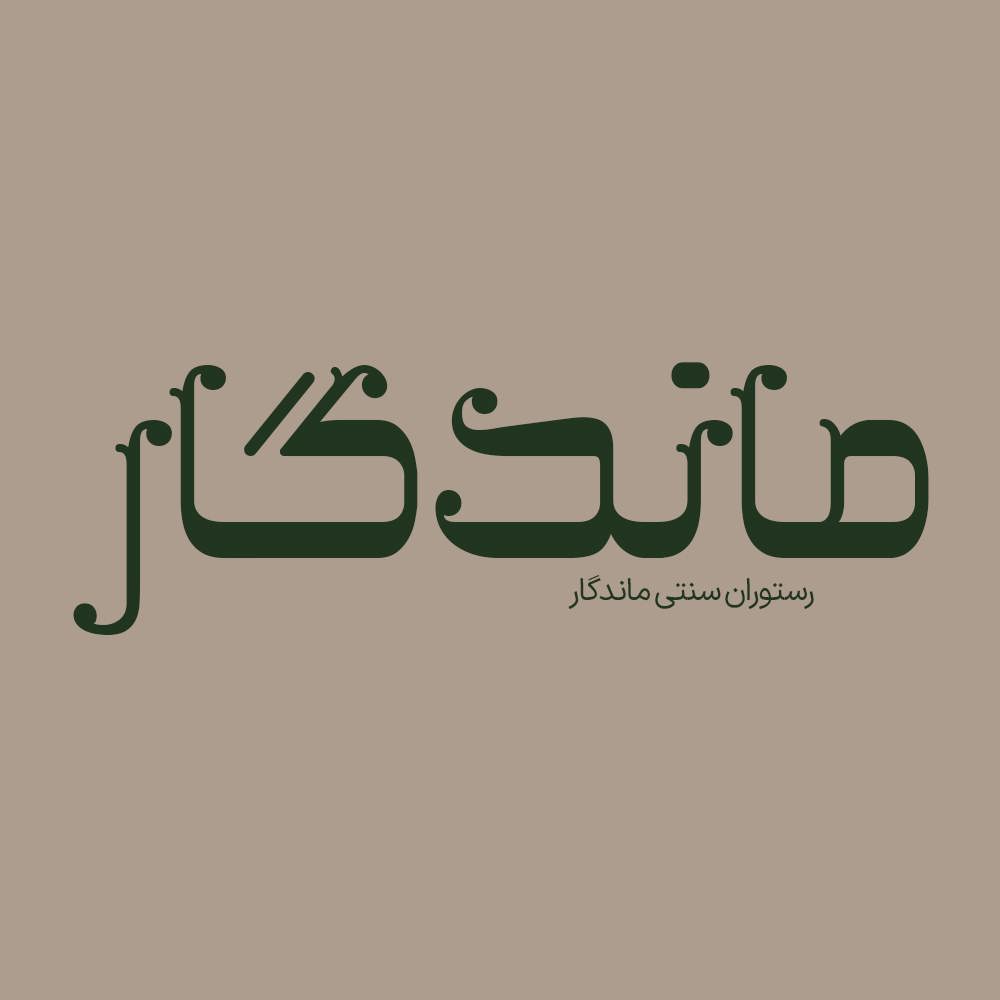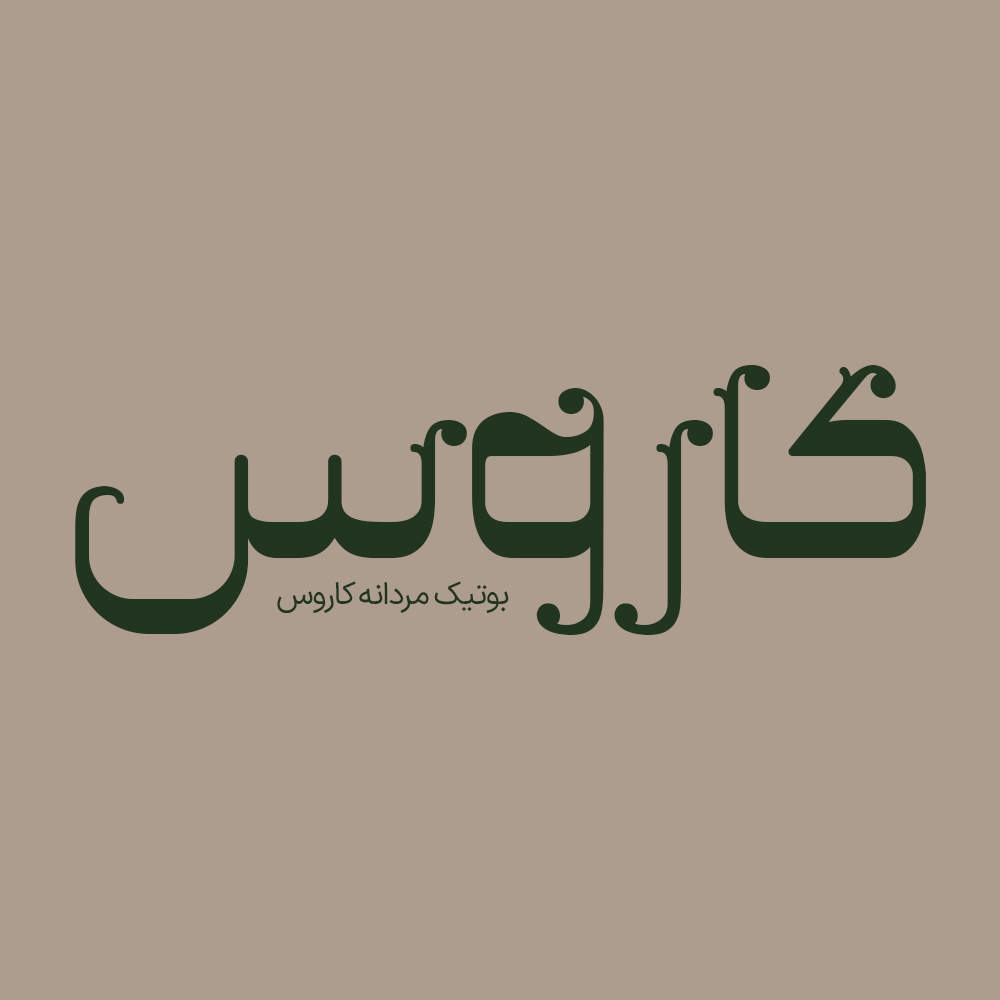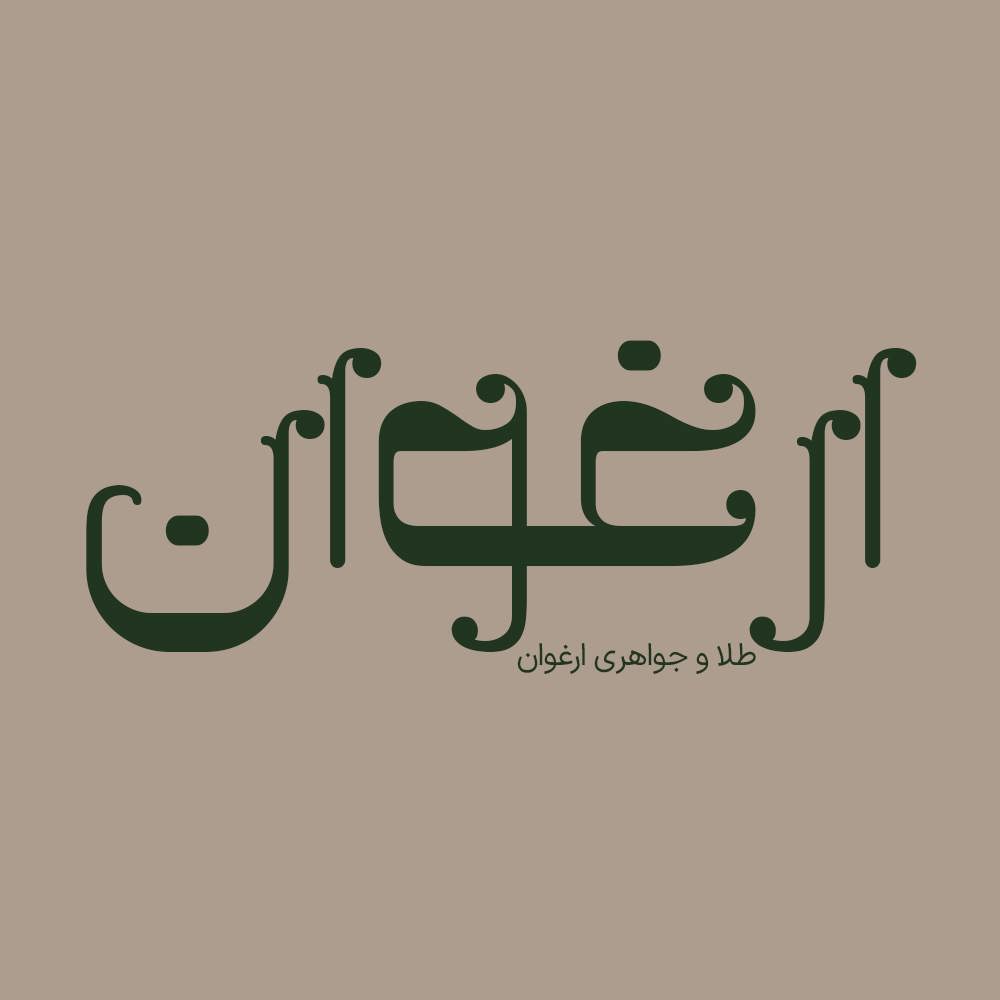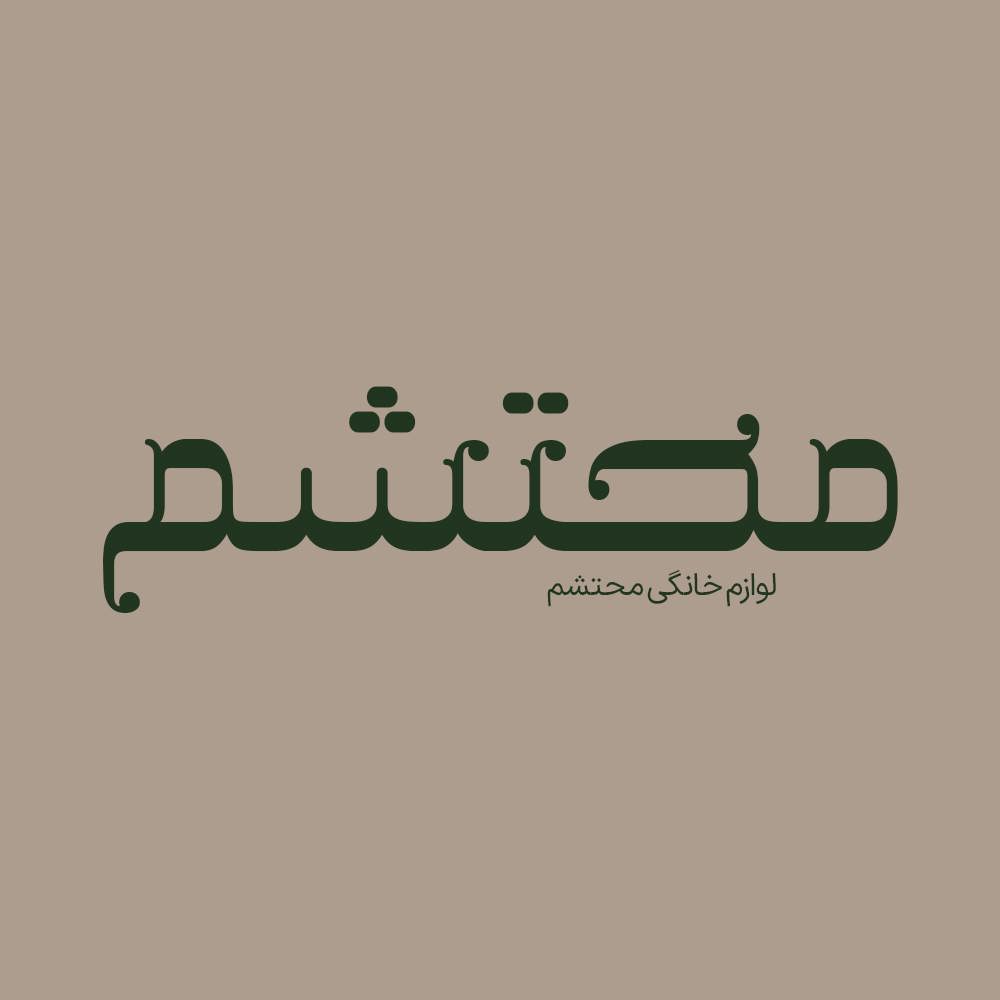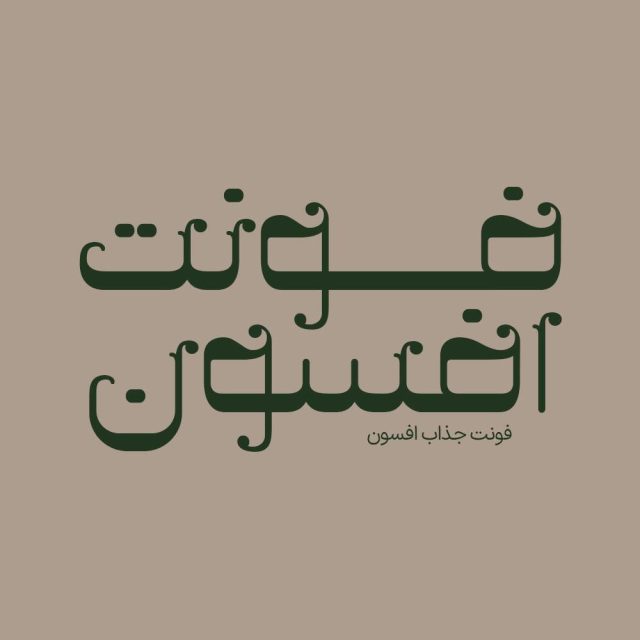
فونت فارسی افسون Afsoon Font
فونت فارسی افسون یک فونت تک وزن با کاربرد طراحی لوگوتایپ و طراحی های مختلف همچون کتاب و تولید محتوای متن های کوتاه و عناوین می…
فونت فارسی افسون یک فونت تک وزن با کاربرد طراحی لوگوتایپ و طراحی های مختلف همچون کتاب و تولید محتوای متن های کوتاه و عناوین می باشد. فونت افسون می تواند در طراحی پوستر ها و بنر های تبلیغاتی کمک بسیاری به شما کند همچنین از فونت فارسی افسون می توانید در تبلیغات محیطی و تابلو چلنیوم استفاده کنید و در نهایت فونت فارسی افسون بهترین گزینه برای طراحی لوگوتایپ فارسی می باشد. در ادامه برای شما نمونه تایپ های این محصول حرفه ای رو آماده کردیم که میتونید مشاهده کنید.
پیشنمایش و نمونه تایپ های فونت افسون